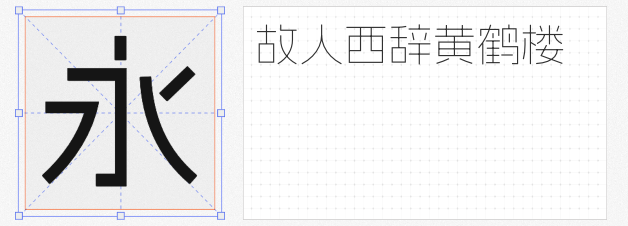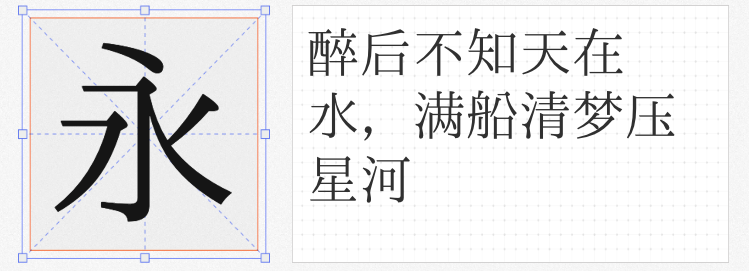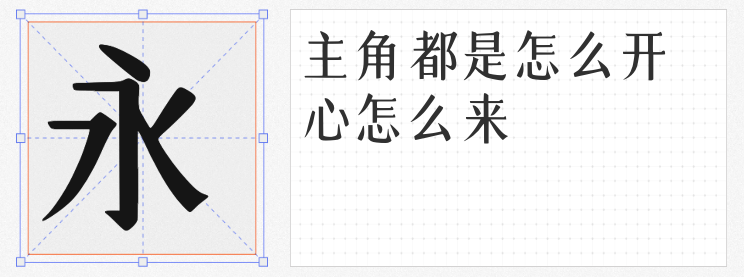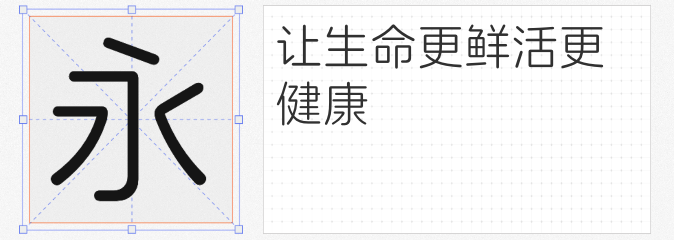
在创意设计领域,字体是传递品牌个性与视觉情绪的关键元素。然而,版权限制与高昂授权成本常让设计师陷入“想用却不敢用”的困境。本文精选四款可免费商用的创意字库,涵盖无障碍创新、风格变轴、宋体革新等维度,助力设计师以零成本实现高阶视觉表达。
作为全球首款中文+注音+盲文三合一字库,阿里健康体2.0以“无障碍设计”突破传统字体边界。其字形亲和稳重,笔画简约流畅,通过计算机算法将盲文点位精准嵌入汉字结构,实现“一触即读”的视觉-触觉转换。这一创新不仅为视障群体提供了更高效的信息获取方式,更在公益海报、医疗健康类设计中传递出科技的温度。例如,在无障碍设施标识设计中,该字体可同时满足明眼人与视障用户的阅读需求,让设计真正“包容万物”。
阿里妈妈方圆体VF以“黑体与圆体的变轴设计”重新定义字体灵活性。黑体版本笔画饱满厚重,布白疏密有致,落笔简练而富有现代韵律,适合科技、金融类品牌的理性表达;圆体版本则以圆润弧线与灵动笔触传递亲和力,轻松驾驭电商、文创等场景。其核心优势在于同一字重下无缝切换风格——设计师无需更换字体文件,即可通过参数调整实现黑体的锋芒与圆体的温柔,大幅提升设计效率与视觉统一性。
由字体家生成的心朵儿体,在保留宋体横细竖粗、笔画装饰性特征的基础上,融入手写体的自然笔触。其横画末端微扬的弧度与竖画收笔的顿挫感,赋予文字灵动气质,既适用于传统文化类设计(如古籍封面、非遗宣传),又能通过色彩与排版创新适配年轻化品牌。例如,在国潮品牌包装中,心朵儿体可通过渐变填充或3D效果处理,让传统宋体焕发时尚生机,打破“宋体=古板”的刻板印象。
基于「IPAex明朝」「霞鹜致宋」优化的水木明体,以中国大陆规范字形为基准,剔除传统宋体中的楷化笔触,强化印刷体的机械美感。其断笔设计、八屋根结构与挑捺饰笔,既延续了宋体的古典韵味,又通过标准化处理确保了屏幕显示的清晰度。适合作为正文字体应用于书籍、杂志排版,或在品牌手册中营造专业严谨的视觉调性,满足设计师对“传统与现代平衡”的极致追求。
免费商用与专业品质并非对立。它们以开放姿态降低设计门槛,让创意回归本质——用文字传递价值,用形式打动人心。无论是商业项目还是个人创作,这些字体都能成为你表达态度的最佳伙伴。